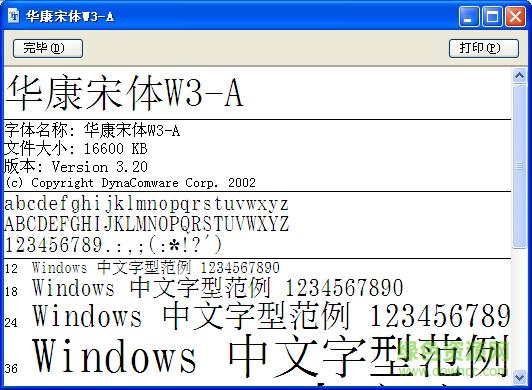
華康宋體W3字體是一款為用戶打造的華康宋體,包含華康宋體W3;字體風(fēng)格樣式名稱:Regular),共有7587個(gè)字符。字符分布范圍:基本拉丁文拉丁文-1補(bǔ)充、拉丁文擴(kuò)充-A、拉丁文擴(kuò)充-B等,更多精彩就在綠色資源網(wǎng)!
華康宋體W3是一款應(yīng)用于廣告設(shè)計(jì)方面的簡體中文字體,該字體大方得體,整體效果非常出眾,并且字庫完整,可以適用于名片設(shè)計(jì)、平面設(shè)計(jì)、廣告設(shè)計(jì)、報(bào)紙雜志、企業(yè)LOGO、商標(biāo)注冊、電視臺(tái)廣告等領(lǐng)域,有喜歡的網(wǎng)友可免費(fèi)下載收藏。
華康宋體W3 Version 3.00字體(字體家族名稱:華康宋體W3;字體風(fēng)格樣式名稱:Regular),共有7587個(gè)字符。字符分布范圍:基本拉丁文拉丁文-1補(bǔ)充、拉丁文擴(kuò)充-A、拉丁文擴(kuò)充-B、國際音標(biāo)擴(kuò)展、空白修飾字母、希臘文和科普特文、西里爾文、一般標(biāo)點(diǎn)符號(hào)、貨幣符號(hào)、似字母符號(hào)、數(shù)字形式、箭頭符號(hào)、數(shù)學(xué)運(yùn)算符號(hào)、零雜技術(shù)符號(hào)、圈型字母數(shù)字、制表符、幾何形狀、零雜符號(hào)、中日韓符號(hào)和標(biāo)點(diǎn)、平假名片假名注音符號(hào)圈型中日韓字母和月份中日韓統(tǒng)一表意文字專用區(qū)中日韓兼容形式半形和全形字符等